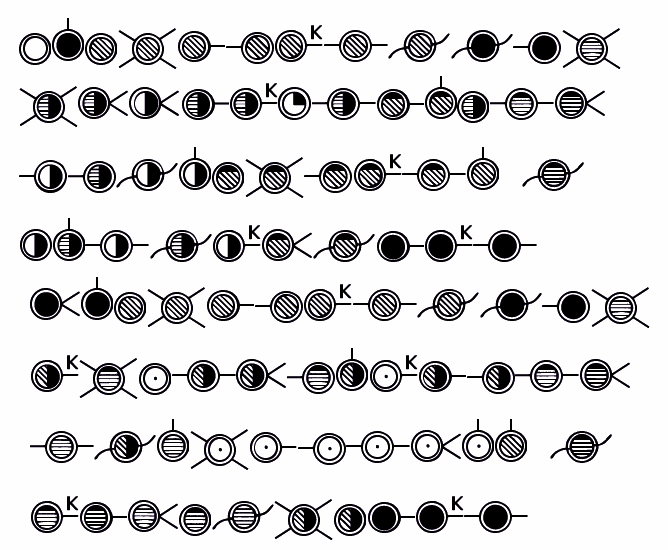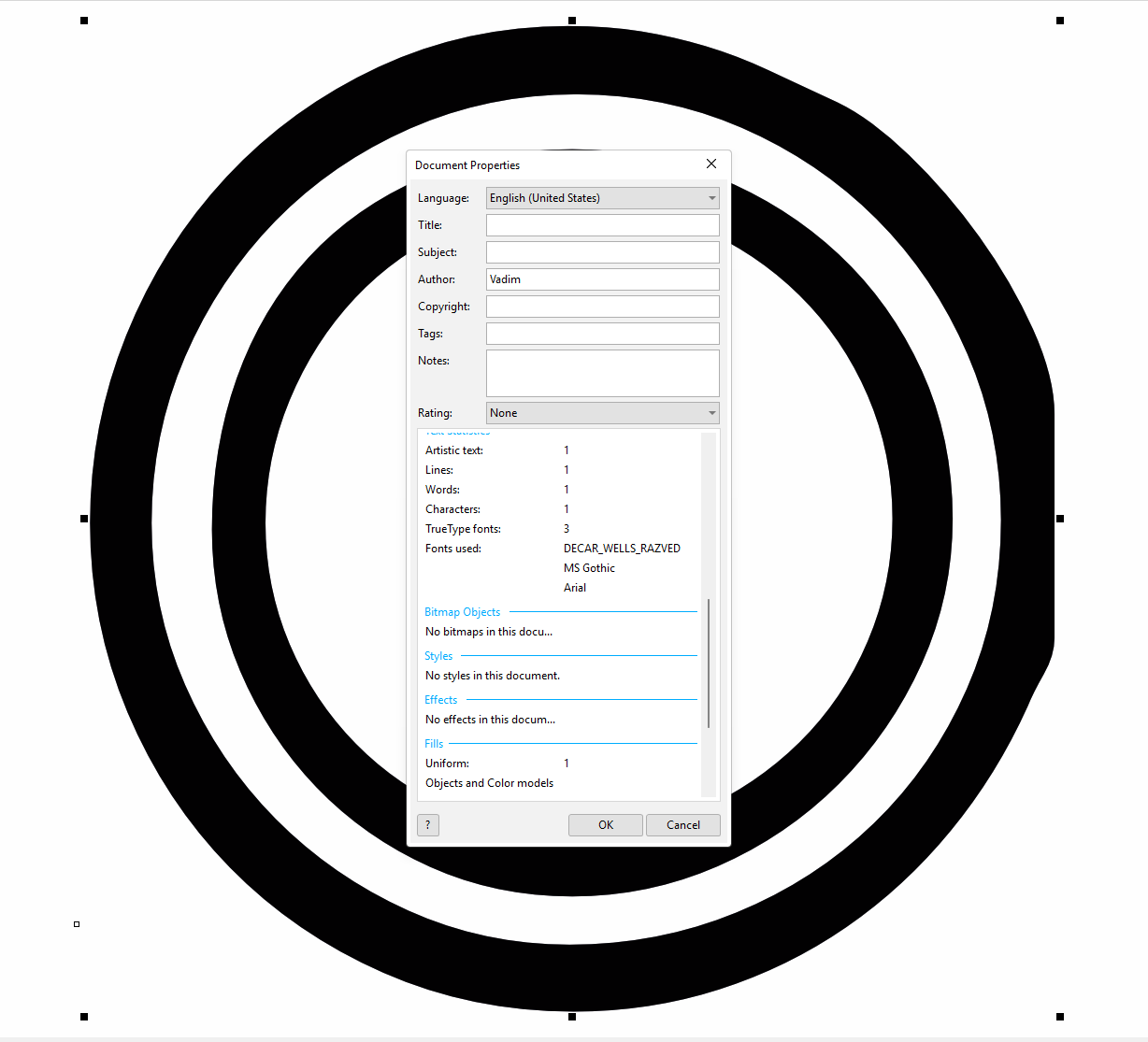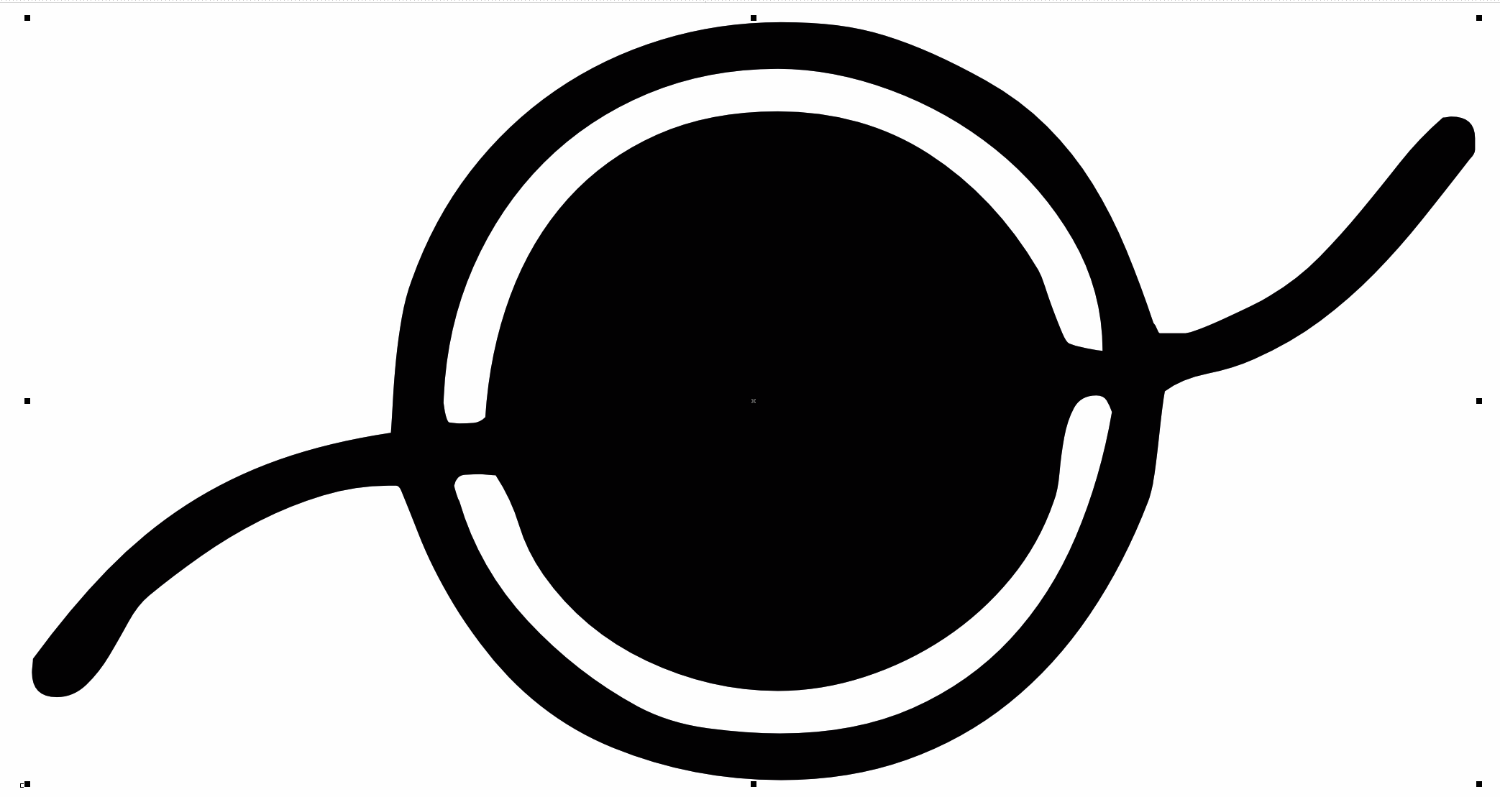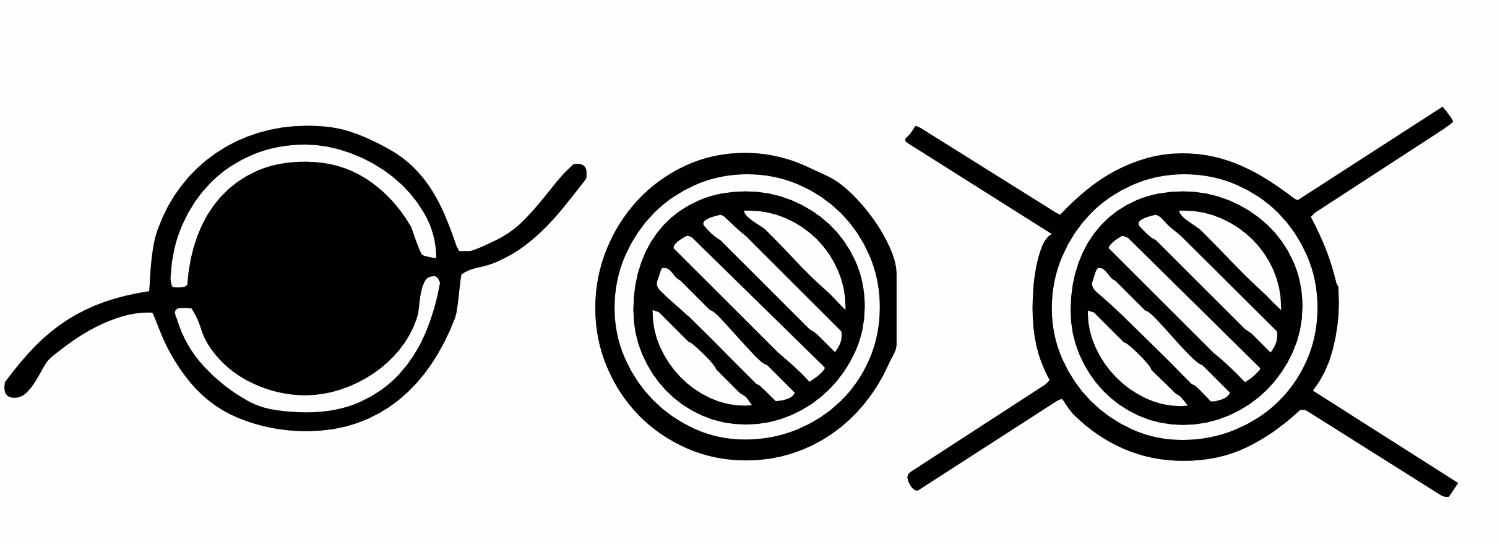
Открылся без алертов, внедрённый шрифт видно. Поменял буквы на цифры и английские буквы - работает. На русском - ариал подставляет.
razved что-то смутно напоминает
Смотрю на глифы - просто очень плохо оттрассированое.
Судя по именам вероятно самоделки какого-нибудь ДЕпартамента КАРтографии 2004 года :)
Поменял буквы на цифры и английские буквы - работает. На русском - ариал подставляет.
D E C A R _ W E L L S _ R A Z V E D W e s t e r n 'opa!)'
и алфавит довольно занятный